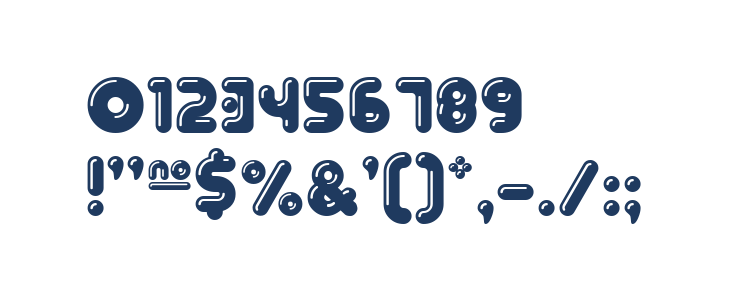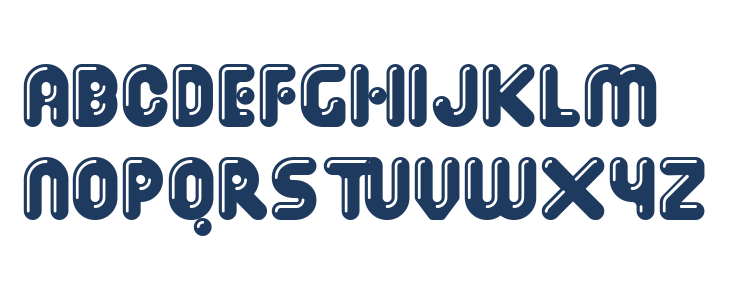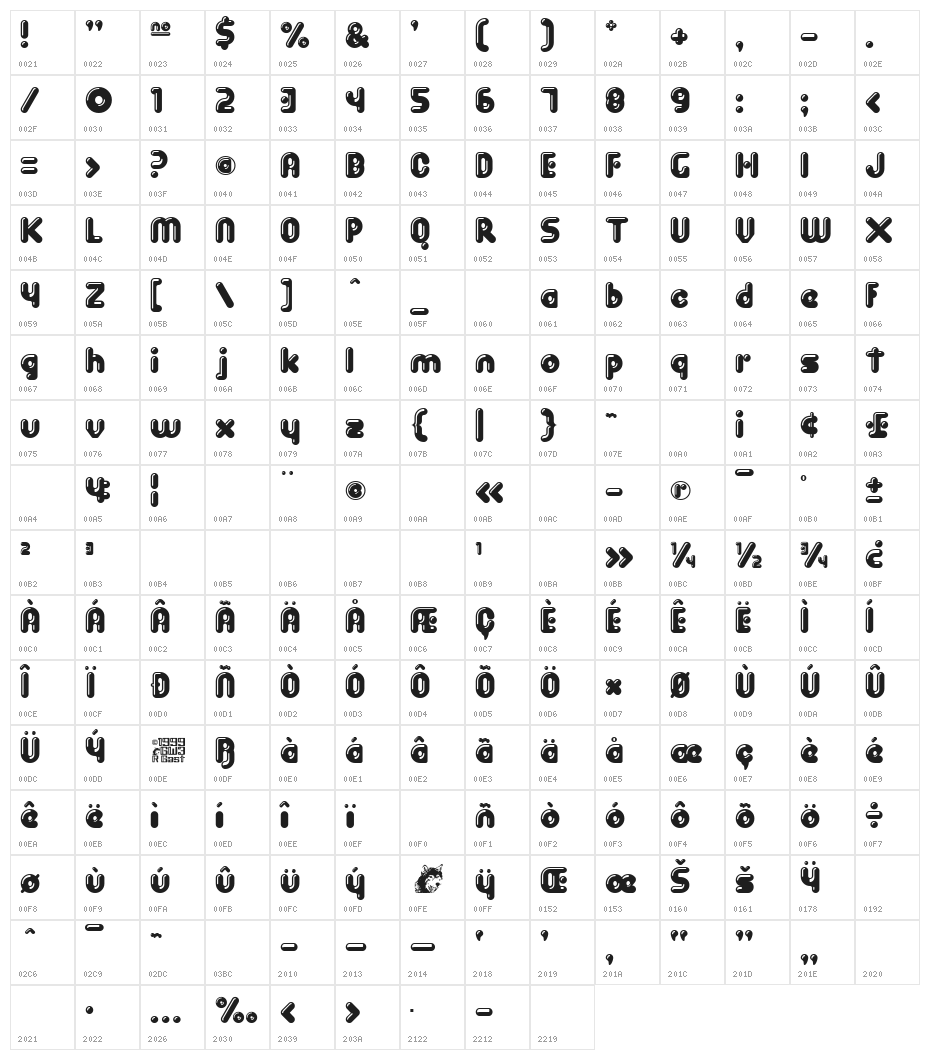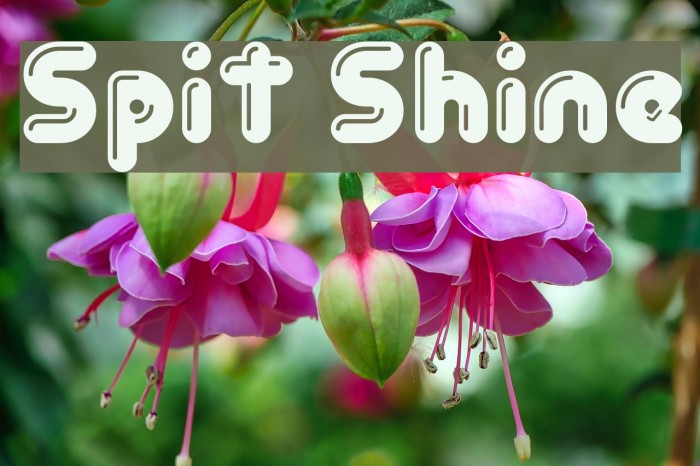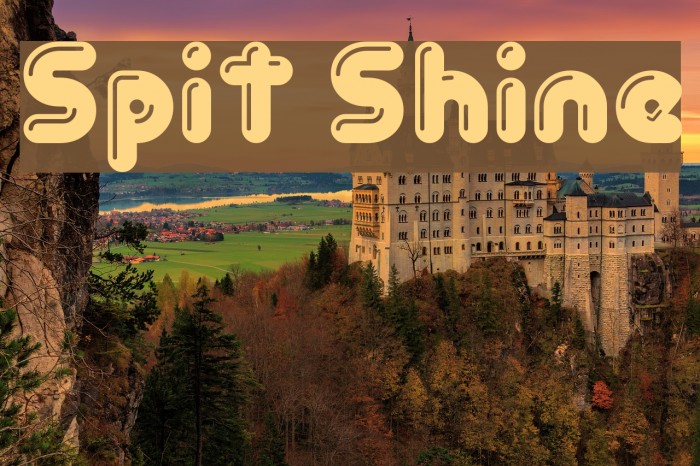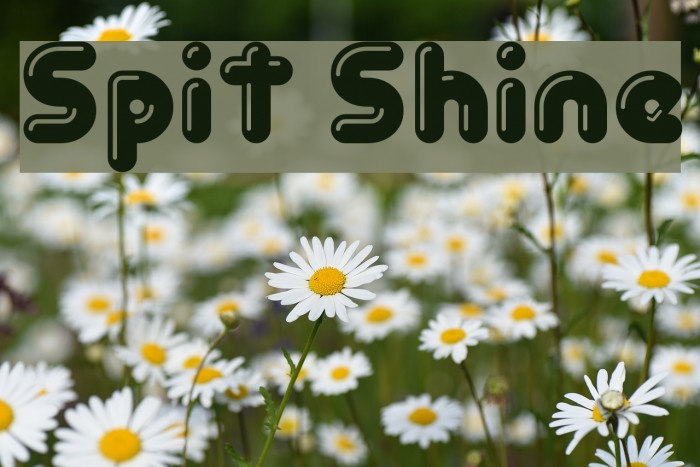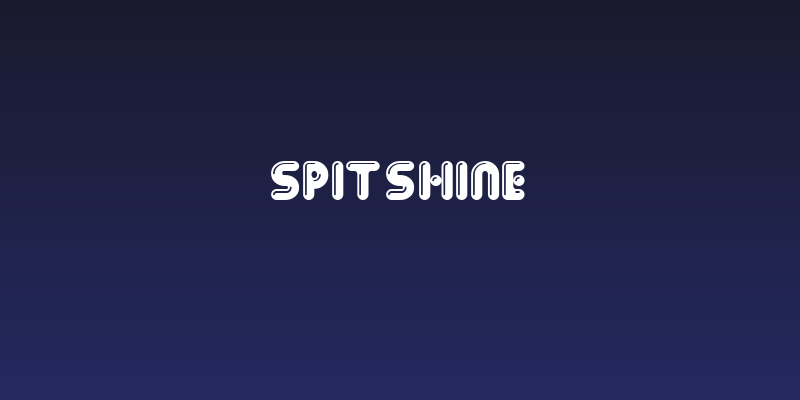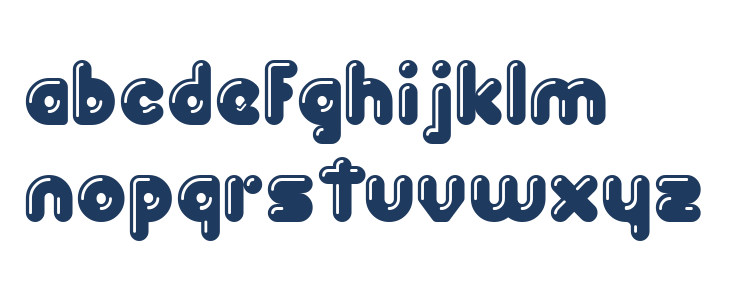
Spit Shine Font
| Stile generale | Playful, Fun, Decorative |
| Progetti proposti | Ideal for children's book covers, playful branding, party invitations, and eye-catching posters. |